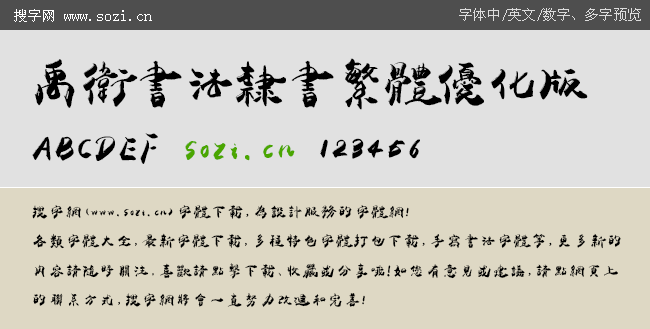
禹衛(wèi)書(shū)法隸書(shū)繁體優(yōu)化版
搜字網(wǎng)給大家提供一禹衛(wèi)書(shū)法隸書(shū)繁體優(yōu)化版中文書(shū)法字體下載。該字體凝重典雅,古樸莊重,具有濃厚的古典氣息,適合包裝設(shè)計(jì)、海報(bào)設(shè)計(jì)、畫(huà)冊(cè)設(shè)計(jì)等廣告設(shè)計(jì)場(chǎng)合使用。
• 風(fēng)格類別: 手寫(xiě)書(shū)法體